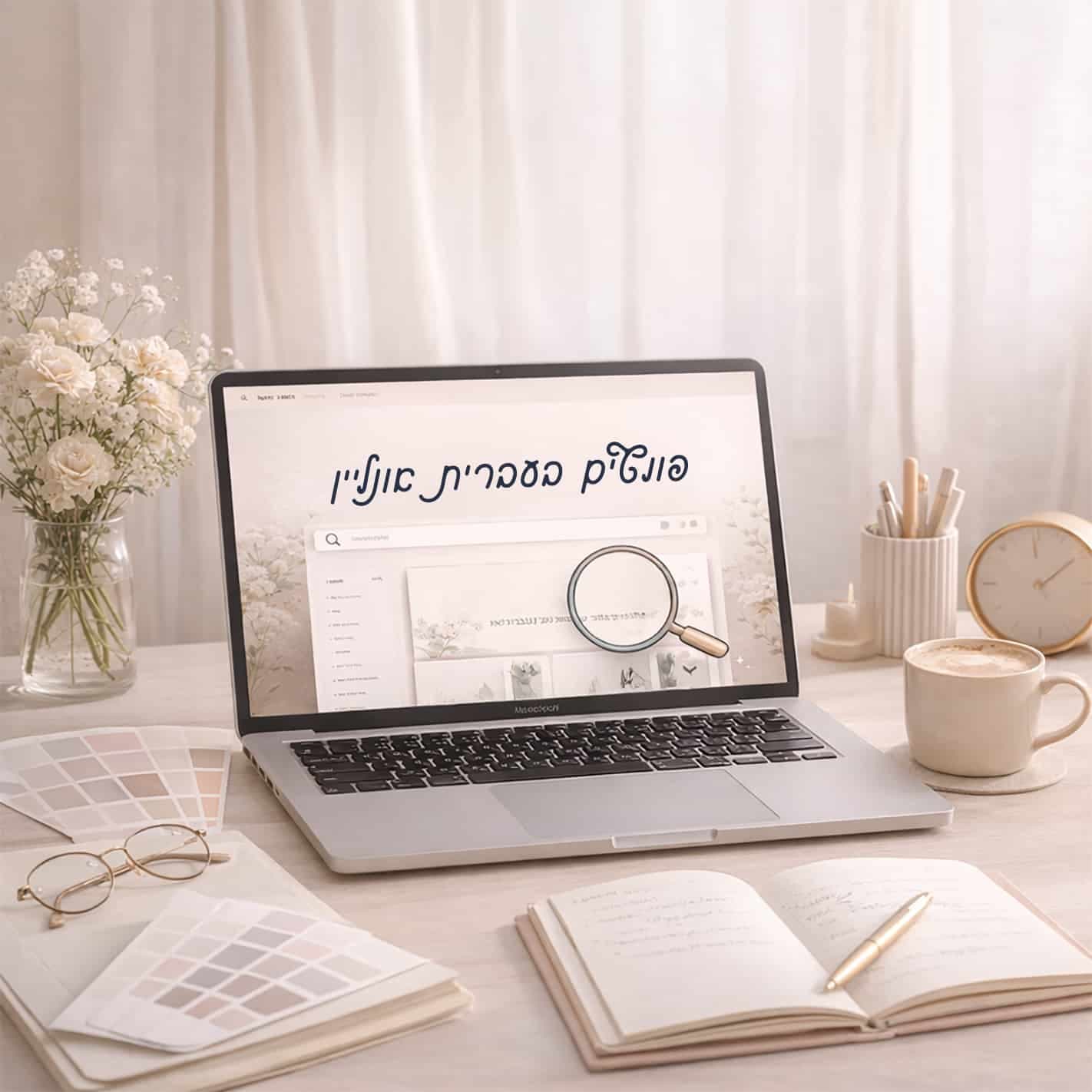
אם אי פעם עמדתם מול מסך המחשב, גוללתם בין עשרות פונטים בעברית אונליין, וחשבתם לעצמכם "איך בכלל בוחרים מתוך כל הים הזה?" – אתם לא לבד. בחירת פונטים בעברית אונליין היא אחת המשימות המאתגרות ביותר בעיצוב, במיוחד כשמדובר בשפה עם מאפיינים טיפוגרפיים ייחודיים כמו עברית. הפונט הנכון לא רק משדר את המסר החזרתי של המותג – הוא גם משפיע על הקריאות, החוויה החזותית, ובסופו של דבר על ההצלחה של הפרויקט כולו.
במדריך זה נעבור יחד על כל מה שצריך לדעת כדי למצוא פונטים בעברית אונליין שמתאימים בדיוק לצרכים שלכם – מהקריטריונים החשובים ביותר, דרך הטעויות הנפוצות שכדאי להימנע מהן, ועד לטיפים מעשיים שתוכלו ליישם מיד בפרויקט הבא שלכם.
הפונט שתבחרו הוא הרבה יותר מסתם אותיות על מסך. בעברית, שפה שנכתבת מימין לשמאל ומכילה ניקוד, דיאקריטים ומאפיינים טיפוגרפיים ייחודיים, הבחירה הנכונה משפיעה על ההצלחה של העיצוב בכמה רמות מרכזיות.
זהות מותגית חזקה: הפונט הוא אחד המרכיבים המזוהים ביותר במיתוג. פונט serif קלאסי משדר יוקרה ומסורת, בעוד שפונט sans-serif מודרני מעביר תחושה של חדשנות ונקיון. כשאתם בוחרים פונטים בעברית אונליין, אתם למעשה קובעים את הטון החזותי של כל התקשורת המותגית שלכם.
קריאות ונגישות: לא כל פונט שנראה מעולה בכותרת יהיה קריא בטקסט רץ. פונטים בעברית אונליין צריכים להיות ברורים גם בגדלים קטנים, עם מרווחים נכונים בין האותיות (kerning) ועם תמיכה בניקוד אם הפרויקט דורש זאת. פונט לא קריא יכול לגרום למשתמשים לנטוש את האתר או את החומר המודפס.
ביצועים טכניים: בעולם הדיגיטלי, משקל הפונט משפיע על זמני טעינה של אתרים. פונט כבד מדי יכול להאט את האתר ולפגוע בחוויית המשתמש. כשאתם מחפשים פונטים בעברית אונליין, חשוב לשים לב גם לגרסאות Web Font המותאמות לשימוש מקוון.
כשאתם יושבים לחפש פונטים בעברית אונליין, יש כמה קריטריונים מרכזיים שצריך לבדוק לפני קבלת ההחלטה הסופית. אלו הם הפרמטרים שיקבעו אם הפונט יעבוד בפועל או רק ייראה יפה בדוגמה.
הקריטריון הראשון והבסיסי ביותר – האם הפונט תומך בכל האותיות העבריות, כולל אותיות סופיות (ך, ם, ן, ף, ץ)? האם יש תמיכה בניקוד אם אתם צריכים אותו? לא כל פונט שמוגדר כ"עברי" כולל את כל הסט המלא. בדקו דוגמאות טקסט עם כל האותיות והסימנים המיוחדים לפני שמתחייבים.
לדוגמה, פונט מיה מציע תמיכה מלאה בעברית כולל ניקוד, והוא גם דו-לשוני – מה שהופך אותו למתאים במיוחד לפרויקטים שדורשים עיצוב בעברית ובאנגלית במקביל.
פונט שנראה מדהים בגודל 48px בכותרת עלול להיות בלתי קריא בגודל 14px בטקסט רץ. כשאתם בוחרים פונטים בעברית אונליין, בדקו אותם בכל הגדלים שבהם תשתמשו – כותרות, תתי-כותרות, פסקאות, הערות שוליים. בנוסף, בדקו איך הפונט נראה על רקעים שונים ובצבעים שונים. פונט דק ועדין עלול להיעלם על רקע בהיר, בעוד שפונט כבד מדי יכול להיראות מאיים על רקע כהה.
גם מעצבים מנוסים נופלים לפעמים למלכודות מסוימות כשמחפשים פונטים בעברית אונליין. הנה הטעויות השכיחות ביותר ואיך להימנע מהן.
הטעות הכי נפוצה היא להתאהב בפונט בגלל שהוא "נראה יפה" בדוגמה, מבלי לבדוק איך הוא מתנהג בפועל. פונט script מהמם עלול להיות לא קריא בטקסטים ארוכים. פונט display מרשים יכול להיות כבד מדי לטעינה מהירה באתר. תמיד בדקו את הפונט בהקשר האמיתי שבו תשתמשו – צרו דף דוגמה עם הטקסטים בפועל, בגדלים האמיתיים, על הרקעים שתשתמשו בהם.
יש מעצבים שחושבים שככל שיש יותר פונטים, העיצוב יהיה מעניין יותר. התוצאה היא בדרך כלל הפוכה – עיצוב מבולגן וחסר זהות. הכלל המקובל הוא לא יותר מ-2-3 פונטים בפרויקט אחד: פונט אחד לכותרות, פונט שני לטקסט רץ, ובמקרים מיוחדים פונט שלישי להדגשות או לאלמנטים מיוחדים. וודאו שהפונטים משלימים אחד את השני ולא מתחרים על תשומת הלב.
פונט טוב מגיע עם מספר משקלים (light, regular, medium, bold, black) וסגנונות (italic, condensed). כשאתם מחפשים פונטים בעברית אונליין, בדקו שהפונט כולל את כל המשקלים שתצטרכו. פונט עם משקל אחד בלבד מגביל מאוד את האפשרויות העיצוביות. לדוגמה, אם אתם צריכים להדגיש טקסטים חשובים או ליצור היררכיה ויזואלית, תזדקקו למשקלים שונים.
אז איך בעצם עושים את זה נכון? הנה תהליך מסודר שיעזור לכם למצוא את הפונטים המתאימים ביותר לפרויקט שלכם.
שלב 1: הגדרת הצרכים והמטרות
לפני שמתחילים לחפש, שאלו את עצמכם: מהי המטרה של הפרויקט? מיהו קהל היעד? איזו תחושה אתם רוצים להעביר? האם זה אתר, חומר מודפס, מיתוג מלא? רשמו רשימה של 3-5 מילות מפתח שמתארות את האופי הרצוי – למשל: "מודרני, נקי, מינימליסטי" או "קלאסי, אלגנטי, יוקרתי".
שלב 2: סינון ראשוני לפי סוג הפונט
על בסיס ההגדרות משלב 1, החליטו על משפחת הפונטים המתאימה. Sans-serif למראה מודרני ונקי, serif למראה קלאסי ופורמלי, script למראה אישי וחם. זה יצמצם את החיפוש שלכם באופן משמעותי. חפשו באתרים המתמחים בפונטים בעברית אונליין והשתמשו בפילטרים לפי סוג.
שלב 3: בדיקת קריאות ותאימות
צמצמו ל-5-7 מועמדים והורידו אותם (או השתמשו בגרסאות ניסיון). צרו דף בדיקה עם הטקסטים האמיתיים שלכם – כותרות, פסקאות, רשימות. בדקו בגדלים שונים, על רקעים שונים, במכשירים שונים. שימו לב לקריאות, למרווחים, לאיכות הכללית.
שלב 4: בדיקת שילובים
אם אתם משתמשים ביותר מפונט אחד, בדקו איך הם עובדים ביחד. צרו דפי דוגמה עם כותרות בפונט אחד וטקסט רץ בפונט שני. הפונטים צריכים להשלים אחד את השני ולא להתנגש. כלל אצבע טוב: שלבו פונט serif עם sans-serif, או פונט גיאומטרי עם פונט אורגני.
בחירת פונטים בעברית אונליין היא תהליך שדורש מחשבה, בדיקה ותכנון. הפונט הנכון לא רק נראה טוב – הוא גם משרת את המטרות של הפרויקט, קריא במדיומים שונים, ומתאים מבחינת רישוי ושימוש. המפתח להצלחה הוא לא למהר, לבדוק את הפונטים בהקשר האמיתי שלהם, ולוודא שהם עונים על כל הקריטריונים הטכניים והעיצוביים.
זכרו: פונטים בעברית אונליין הם כלי עבודה חשוב במיוחד בשפה עם מאפיינים טיפוגרפיים ייחודיים. השקיעו זמן בבחירה הנכונה, ותקבלו תוצאה שתחזיק לאורך זמן – עיצוב מקצועי, זהות מותגית חזקה, וחוויית משתמש מעולה.